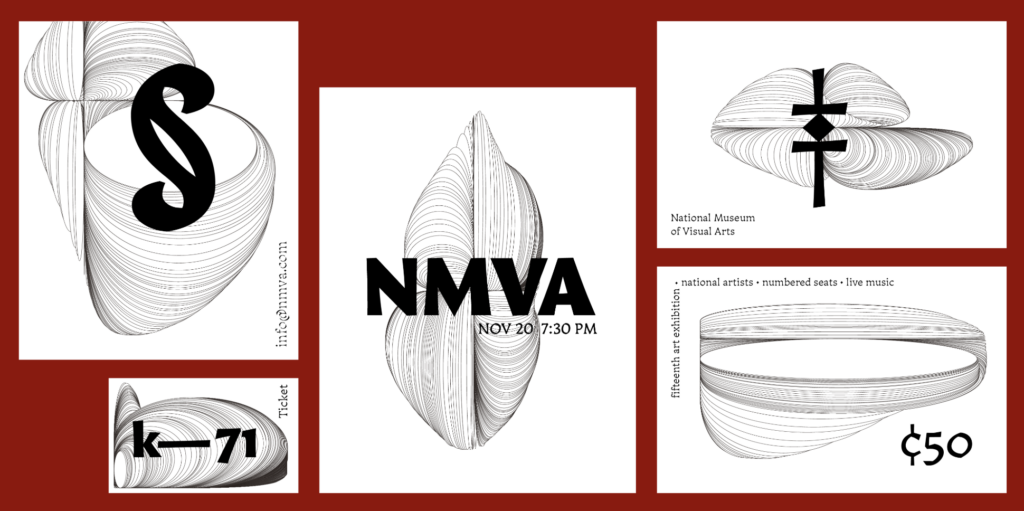
Mazumbá, el candombe afrouruguayo hecho tipografía
Hará cosa de tres años, publicamos en estás páginas una entrevista a Fernando Díaz y Matías Di Iorio, fundadores de Reset Type, que por aquel entonces, noviembre del 23, se presentaban al mundo.
Hoy son ya una realidad asentada dentro del panorama tipográfico latinoamericano. Durante estos años, tan sólo tres desde su fundación, pero laboriosos a la vista de los resultados, han ido dando forma a un catálogo de tipografías retail rico y versátil que oscila entre la funcionalidad y la expresividad. Además, cuentan ya con un nutrido portfolio de tipografías custom de lo más variado.